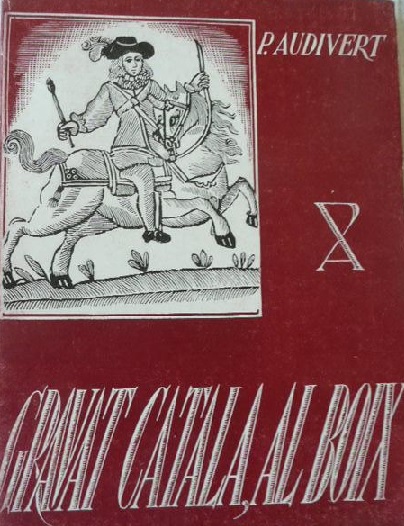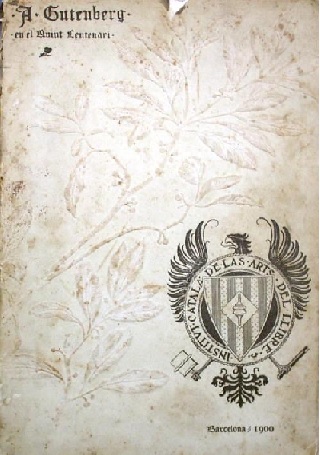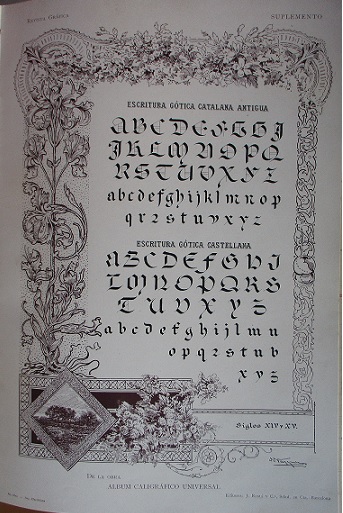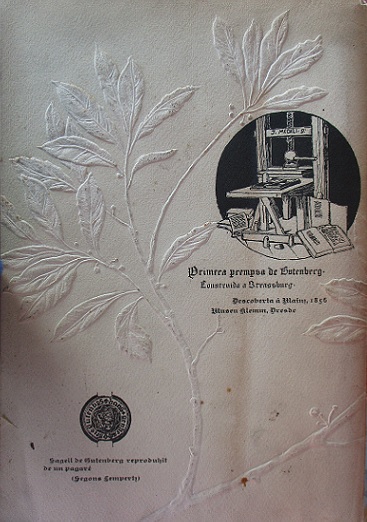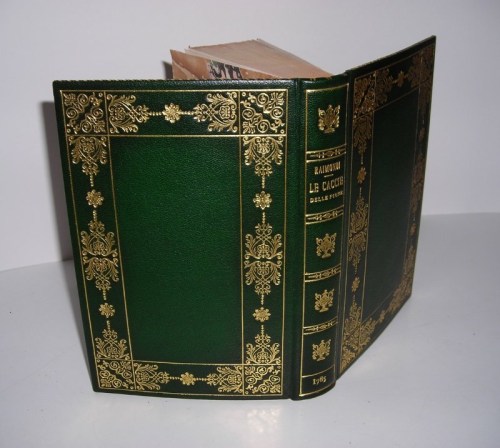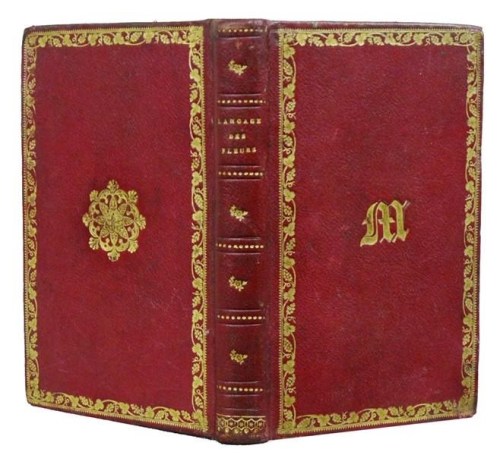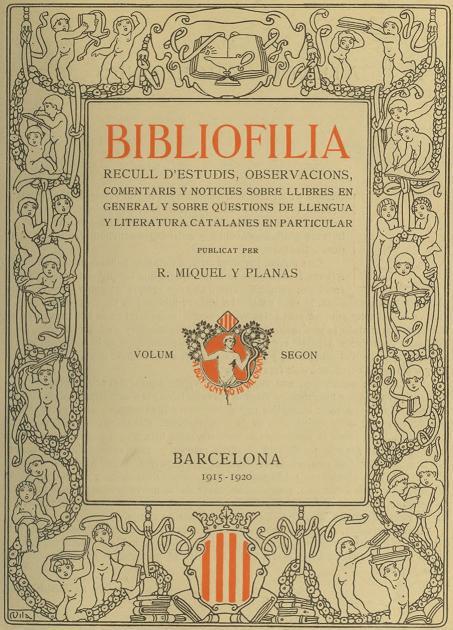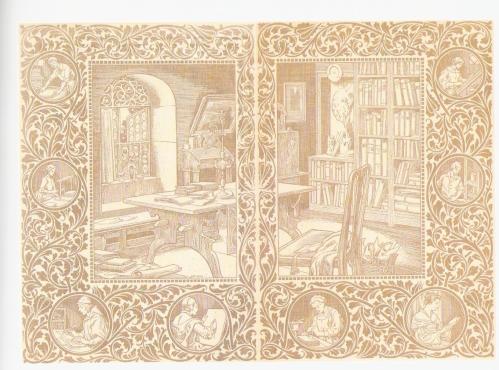
“ És en la xilografia catalana on trobarem sempre la plenitud d’una imatge que té molt de llegenda; és l’expressió serena, sempre assaonada per l’alè de la terra. Catalunya, poble d’artesans, on els oficis, àdhuc els més rutinaris, sempre han tingut la més bella i acurada perfecció, és un dels llocs on el gravat al boix tingué més tradició, una tradició de segles de treball, una recerca per dir quelcom per mitjà de l’estampa impresa, és la superació d’un ofici ple de dificultats, vençudes amb tota noblesa, en el qual es palesa la personalitat de tot un poble.
La imatge en els boixos catalans és una de les més riques. El tema podrà ésser sempre el mateix, però en la repetició la imatge serà sempre diferent: Mirem si no una estampa de Sant Jordi, tantes vegades repetida, i sempre diferent: és la concepció de l’espai dintre de la imatge, són els petits moviments de línies i formes, amb el complement de diferents perspectives, és sempre la visió personal de l’objecte que s’interpreta, allò que li dóna plenitud de cosa feta, modalitat ben catalana.
Composició serena, expressió de sentiment popular, perquè parla el llenguatge del poble i es troba dintre del poble, composició d’artesà, que, dintre de la seva ingenuïtat, té una idea certa de la importància i valor dels blancs i els negres en l’estampa, és d’un home desinteressat que està al marge del intel·lectual, és l’expressió venerable d’un artesà anònim que ens parla sempre amb les seves mans plenes de saviesa.
Aquesta demostració de la imatgeria nostra és ben catalana, car si comparem els nostres boixos amb els dels d’altres països trobarem sempre una diferència substancial. Els italians seran més clàssics, més afinats, sempre producte d’un sentit d’escola; els alemanys i els holandesos, concrets, sàviament saturats d’una imatgeria rica, espremuda fins a la última gota, és l’obra acabada de l’artista que s’expressa per mitjà d’un ofici portat al màxima perfecció a fi d’aconseguir l’obra. En ells ho trobem tot fet, no tenen aquella mena de suggestió que té el boix català que fa que el que el contempla sempre pugui afegir-hi quelcom més: és la insinuació d’una cosa que no acaba mai d’expressar-se i sempre s’hi troba present.
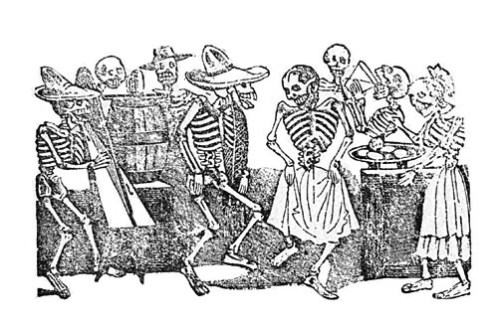
José-Guadalupe Posada, El Jarabe en Ultratumba
I és que mentre en altres països el gravat fou gairebé sempre treballat per artistes que en feren un ofici, adés realitzant les seves obres, adés reproduint les dels altres, a Catalunya seguia essent la feina d’un artesà anònim que interpretava les imatges d’un dibuixant, era la col·laboració de dos homes que es nodrien de les inquietuds i gustos del seu moment.
Aquestes inquietuds, expressades moltes vegades fent concessions als gustos del poble, és el que dóna un caient tan humà a les xilografies catalanes, s’alimenten de saba popular, tenen tota la ingenuïtat de voler agradar i estan fetes amb una saviesa que fa que les puguem apreciar com verdaderes obres d’art sense que llurs autors s’ho hagin proposat. Aquesta diferència substancial amb l’obra preconcebuda fa que hom pugui elevar-la a la categoria d’art pur”.
Gravat català al boix, amb seixanta reproduccions, quatre gravats originals i una auca d’arts i oficis, Pompeu Audivert, Biblioteca Catalana – México, D.F./ B. Costa i Amic Editor, 1946; p.21-22.
Marca d’impressor d’Aldus Manuzio
“ Los que como Ud. Somos aficionados a librajos y papeles viejos, solemos experimentar de vez en cuando algo de esa alegría y emoción inefables que sintieron nuestros esforzados navegantes al descubrir por vez primera las playas del Nuevo Mundo. ¿ No es verdad, amigo mío, que cuando por acaso, en medio de un montón de inepcias condenadas al nacer a rodar por baratillos, a ser pasto de ratones o a envolver cominos, tropezamos con una Aldo Manucio, un Gryphio, un Plantino apud Moretum, un Caxton, …, o con alguno de esos incomparables y codiciados Elzevirios, … gozamos de una felicidad suprema, que comparada con esas grandes pasiones destinadas a satisfacer algunas raras veces y por breve momento el corazón humano, excede de todo un cielo a los goces del amor, de la ambición y de la avaricia? – Cierto es que para el verdadero bibliófilo ( que no se confunde nunca con el falso, el pseudo-bibliófilo, el coleccionador que sólo busca y colecciona por el gusto de atesorar, que en medio de su espléndida biblioteca se aparece al eunuco entre las odaliscas de un harén: el mercachifle literario que adquiere para revender y lucrar; el tonto, pues de todo hay, que tiene libros por aparecer discreto); para el bibliófilo auténtico, para el amateur pur-sang, como dicen los franceses, el hallazgo de un libro raro o de un manuscrito curioso es superior a cuantos juguetes y brillantes señuelos se han inventado para entretener y atraer y fascinar las miradas de esa caterva de niños grandes que se agita y afana en este pícaro mundo, el que, dicho sea de paso, sería una trastienda del infierno, si no hubiera libros.”
Article: “Entre el conocimiento y la bibliofilia”, de Fco. García-Jurado, reproduïnt un text de Camús. En el vlok Reinventar la Antigüedad: https://clasicos.hypotheses.org/317
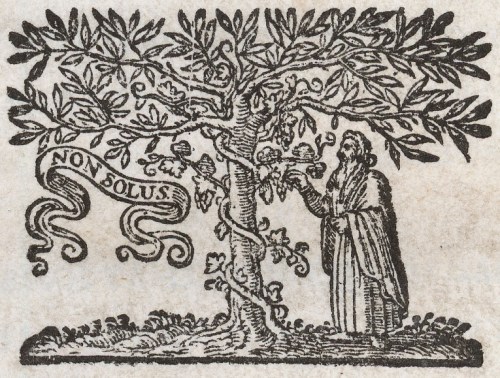
Marca d’impressor d’Elzevir
Revista Gráfica 1900
“ Ja fa alguns anys que tot quan se refereix á las arts anomenadas de una manera general Arts del llibre, es obgecte de particular atenció, y res d’estranyar es que aixís sía; ans al contrari, inesplicable resulta que per tant temps lo trascendental invent de l’Imprempta hagués devallat tant al desota de las demés produccions del home en totas las brancas de l’Industria. Aqueixa s’ha vist sempre, en més ó en menys, á través dels capritxos incoherents de la moda, abellida per les aplicacions decorativas de las arts plásticas. Mentres se pretenía exornar lo més vulgar y prosaich obgecte, necessari en las prácticas de la vida, lo llibre, lo vehicul de la idea, de totas las doctrinas, fconcretament, no solsont de las evolucions que tot ho capgiran, impuls de tots los avensos, doll inacabable de sanitós plaher que enlayra á l’inteligencia, ferm consol del que sofreix, sanitosa distracció dels felissos pobres d’esperit, y en mitj de tot, nombrosa reunió d’industrias, de travalls en que s’afanyan milers de criaturas fent trasbalsar milions, fonament de moltas fortunas; lo llibre, originat y nascut de un procediment artístich; lo llibre, que en son comens era un joyell, había acabat per esser un producte industrial groller y xavacá, fora de raríssimas excepcions ab que distingidas personalitats mantenían la tradició dels bons temps de l’Imprempta, fentne esperar una salutable regeneració, que, si no es arribada á realisarse en tot, se iniciá no fa molts anys, y s’exten, creix y se desenrotlla, comensant a posar lo llibre al nivell de las demés obras del home, no sols concretament com travall d’impressió, sino també en tots los procediments y materials que intervenen en los elements que d’ell se’n derivan.
Revista Gráfica 1900, anunci.
Lo despertament ha sigut ben general: lo meteix á l’América del Nort, á França que á Inglaterra, que á Austria, que á Alemania y que á Italia. Com succeheix en las demés aplicacions de las arts als productes industrials, que l’observació y l’estudi de las obras creadas en épocas ja llunyanas dona per resultat lo formar un comensament d’istil propi de la nostra, la devoció als exemplars de las primeras prempsas contribuheix á retornar al llibre d’avuy quelcom de las qualitats que aquells tenen, y de nou, tot quan s’hi relaciona, tendeix á esdevenir un travall artístich en lloch d’esser lo mer resultat de un ofici manual en que la inteligencia y lo sentiment de la forma, del color y de l’armonía poch ó res tenen que veure.
Dintre de la tradició establerta per las obras clásicas de l’Imprempta, ne deriva, lo meteix que de tots los caracters escrits, més ó menys exótichs, la imaginació d’avuy, tipos y formas que responen al afany de produhir alguna cosa nova; camí que á l’avenir conduhirá indubtablement á la creació de l’original que are tant admirém en lo de sigles enrera”.
J. Lluis Pellicer, en l’editorial de Revista Gráfica 1900, p.1-2; editada per l’Institut Catalá de les Arts del Llibre.
( curiosament, per les més de 40 pàgines dedicades a anuncis ja val la pena la revista)
Revista Gráfica 1900 ( revers)
χφ               χφ               χφ               χφ
Enquadernació de Vicente de Diego
“ Hay muchas clases de libros y  no todos necesitan ni merecen amor. Los hay de usar y tirar; no faltan los que se reducen a simples ajustes de cuentas con otros o con uno mismo; algunos no valen más que como mensajeros; otros no son más que cestos de noticias y los hay cuya existencia no está justificada más que para su autor. Pero los hay también de leer y guardar, para volver a descansar en ellos; de tener, para entrar y salir de ellos; de guardar, para convivir. Y, para ser libros de amar por sí mismos, todos ellos necesitan un lecho acogedor y suave para una tipografía discreta, variada y elegante; una distribución del texto armoniosa y ajardinada; acaso unos complementos gráficos que acompañen sin distraer ni aturdir; un formato que no les impida ser un objeto eventualmente a mano y una encuadernación ( industrial, artesana, fina, original) hermosa. Resultan todavía insustituibles en la vida del hombre de cultura, que hoy pudiera ser cualquiera. No hace falta pedir lo imposible. Sólo un pergamino rubio y blando, más bien sin arrugas, o blanco y duro, ‘ a la romana’, pero sin tensiones deformadoras; una pasta española, acaso jaspeada, con guardas de papel de ondas o de guijarros; un papel labrado o pintado sobre un folleto del XVIII; ojalá, quien pudiera, una pasta valenciana; o un tafilete azul, verde, con frecuencia rojo con un filete en recuadro y cuatro florones dorados en las esquinas. A partir de ahí, todos los sueños. Gracias a la encuadernación el libro es una fiesta. Y no sabría decir si el amor al libro – y en buena medida, la cultura- empieza o termina en la encuadernación”.
Encuadernación y destino del libro ( Loa y guía de pequeños y grandes coleccionistas)”, article de Manuel Carrión Gútiez, a Bibliofilias ( Exposición con motivo del 38º Congreso Internacional y 21ª Feria Internacional de ILAB, Madrid, 2008), pp. 65.
Estampació d’època en plena pell, tafilet vermell, amb estampacions en or en cobertes i llom.
Read Full Post »
Miquel y Planas, durant els anys del periple de Vila, inicia i elabora la seva revista intitulada BIBLIOFILIA. Diem ‘seva’ amb una doble intenció, car no només n’es l’editor, sinó també l’autor de tots i cadascun dels articles. És una mena de petita enciclopèdia sobre el llibre en general i, en particular, sobre qüestions de llengua i literatura catalanes, en què l’autor manifesta el seu coneixement del tema.
Iniciada al juny del 1911, el primer volum abraça tota la producció des del 1911 fins al 1914. Tot i que la il·lustració no hi és important, s´hi reprodueixen alguns gravats facsímils d’edicions antigues. Però allò per la qual cosa se la reconeix sobretot és la portada. L’autor n’és Joan Vila.
Una orla d’amorets enjogassats amb una colla de llibres i entortolligats amb cintes i amb garlandes de flors, presidia al capdamunt per un llibre i un llantió, símbols del saber, i a la part inferior per l’escut de Catalunya, emmarcat el títol i el logotip de l’editor, amb la seva cèlebre màxima ‘A bon seny no hi val engany’ Els amorets de Vila acabaran sent un element clarament identificador seu als llibres de bibliòfil de Miquel y Planas. Perquè no sols en dissenya l’obra, sinó que hi crea un alfabet de caplletres decorades on l’element ornamental és un amoret. Al primer volum de BIBLIOFILIA, la intervenció de Vila es limita a la portada esmentada, a la caplletra A del frontispici, impresa en vermell, i a la taula de noms final, on apareixen totes les caplletres dels amorets.
En canvi, el segon volum, del període 1915-1920, presenta una portada idèntica i una caplletra C al frontispici, però, a més, tots i cadascun dels articles s’enceten ja amb una caplletra. La decoració, doncs, en aquest cas és molt abundant. I no sols això, sinó que també sorgeix un nou element decoratiu que forma part de la mateixa sèrie: quatre capçaleres i tres vinyetes d’amorets jugant amb llibres, pintant-los, tirant-se’ls pel cap, etc., tot emmarcat per les mateixes cintes i garlandes esmentades abans, que es poden veure a les taules d’articles, d’il·lustracions i de noms. D’una gran agilitat i un moviment subtil, aquestes figures atorguen un caire molt peculiar a la revista de Miquel y Planas.
Ara bé, no sols és Vila qui contribueix a fer possible aquesta publicació. Les guardes són a càrrec del seu mestre, Josep Triadó, i les cobertes en relleu de color roig, són obra de Joaquim Figuerola. Quatre noms que, com comprovarem al llarg d’aquestes ratlles, mantindran sempre una relació”.
D’Ivori. Bibliofília i exlibrisme”, de Pilar Vélez en el llibre: D’Ivori. La màgia de la il·lustració, de Josep M. Cadena, M. Castillo i Pilar Vélez. Editat per l’ Ajuntament de Barcelona, dins la col·lecció El traç que alliçona (nº 2),p.
℘          ℘          ℘          ℘          ℘          ℘          ℘
La bibliofilia, desde luego, es un hecho de todos los tiempos. Los testimonios encarecen a los bibliófilos de Alejandría, las bibliotecas inestimables de los humanistas de los siglos XV y XVI – recuérdese, por ejemplo, la del Marqués de Santillana, catalogada por Schiff -. Los mecenas arruinados en su afán por acumular libros, los modernos coleccionistas que luchan tanto con el precio de los libros como con el espacio para guardarlos, nos hablan de esta pasión y de sus variantes. Y en los días actuales este amor, desgraciadamente, pareciera haber entrado en una faz de posible explotación comercial, con lo que ello tiene de anulador, porque ya no sólo se prefabrican ediciones para bibliófilos, sino además también se especula con la rareza. Por eso Valéry, en el ensayo Livres, confesaba que para él la pasión libresca no
residía en lo raro de los libros. ‘La rareza – escribía – no me afecta excesivamente. No es sino una noción abstracta e imaginaria, si por otra parte no está sólo en casa del rematador. Los ojos no saben que tal ejemplar es único. Tocarlo no alegra, no hace gozar de modo especial. Yo, en caqmbio, quiero los libros sólidos i ‘confortables’ como se los hacía en el siglo XVIII’ “.
CASTAGNINO, Raúl H.: Biografía del Libro. Editorial Nova, Buenos Aires, 1961. Colección Compendios Nova de iniciación cultural, nº 42, pp.123.
Read Full Post »
juvenal
“ Quan els nostres esclaus sàpiguen llegir, ja no seran els nostres esclaus. (Juvenal, 42-125).
“Estima el llibre pel llibre, mes procura que sigui bo”. ( San Jerónimo, 331-420).
“Los libros no oyen, pero hablan”. (Góngora, 1561-1627).
nicolas-antonio
“No hay placer mayor que el coleccionar libros… y leerlos”. (Nicolás Antonio, 1617-1684).
“La lectura ens aparta del món i, no obstant això, com més llegim més ens endinsem en ell”.(Victor Alfieri, 1749-1803).
“Una casa sense llibres és com un jardí sense flors”. (Proverbi àrab).
“La passió pels llibres és la més noble de les passions”.(Ling-Po, 1823-1901).
“Qui nomès llegeix un llibre, no sap més que una cançó”.(Popular català)
“Un bon lector fa un bon llibre”.( Emerson, 1803-1882).
apelles-mestres
“Llibre, amic el més fidel, sempre obert a qui et demana…”(Apel·les Mestres, 1854-1936).
“No digas que un libro es caro si el libro es antiguo y raro”. (Rodríguez Marín, 1854-1943).
“Compra llibres encara que no siguin els meus”. (Bernard Shaw, 1856-1950).
cau-ferrat
Cau Ferrat creat per Rusiñol
“Els llibres, per a mi, no són mai cars ni ‘baratos’, són bons o són dolents”.(Santiago Rusiñol, 1861-1931).
diccionari-aguilo
“He passat la vida entre llibres, i si una altra vida tingués faria el mateix”.(Marian Aguiló, 1835-1910).
“Un bon llibre no es paga en diners”.(Popular català).
bibliophrasis1
Frases de l’opuscle : “ Bibliophrasis. VII Feria anual del Libro de Ocasión. Antiguo y Moderno”, Barcelona, 1958. Obsequio a los favorecedores de la Feria. (Obsequi que ja fa anys que ni donen ni fan).
antologia-de-sitges1
“ Bueno, vamos a abrir las puertas de mis librerías. He insinuado ya que soy un bibliófilo modesto. Aquí no daréis con incunables ni con primeras ediciones. Aquí viene, sencillamente, el buen libro tanto de contenido como de presentación”.
ROBERT MESTRE, José: Divagaciones de un bibliófilo, disertación de … , en la Asociación de Bibliófilos de Barcelona, Barcelona , 1964.
Editat l’any 1965, imprés a Filograf (R.G.M., Instituto de Arte Gráfico de Barcelona), 1965. Opuscle de 7 pàgines amb dibuixos de Emilio Ferrer.
filograf2
exvlokis-color
Read Full Post »
rosa vera 1
“ A partir de 1948 neix a Barcelona una altra iniciativa en el camp de la bibliofília que deixarà una forta empremta. Em refereixo a les edicions de La Rosa Vera, que fan una labor extraordinària en la promoció de les edicions d’alta qualitat, tant de llibres de bibliòfil com de sèries de gravats. La iniciativa parteix del gravador i pintor Jaume Pla Pallejà (1914-1995), i tot se- guit compta amb la bona acollida i el patrocini econòmic del col·leccionista i mecenes Víctor M. d’Imbert. L’aportació a la bibliofília de les edicions de La Rosa Vera és una de les més notables per l’obra realitzada i la promoció que representa de l’expansió del gravat, al qual es van dedicar alguns artistes reconeguts que el practicaven per primera vegada.
rosa vera 2
Jaume Pla destaca no només com a gravador, que domina amb una gran perfecció totes les tècniques i tots els procediments, i com a promotor del gravat i de les edicions selectes, sinó alhora com a teòric d’aquestes matèries en diversos llibres i articles, en els quals es mostra amb uns criteris molt precisos i estrictes, de gran exigència. És un dels pocs que ha exercit en aquest camp una crítica responsable i documentada. En el seu llibre Técnicas del grabado calcográfico ( 1956   la primera edició) van aprendre a gravar moltes persones d’aquí i d’altres països. L’autor, en  un capítol del llibre, teoritza potser per primera vegada sobre el que és la bibliofília: aquest capítol  ha estat una font bàsica per a molts dels qui després hem tingut una predisposició especial per l’estudi i el col·leccionisme de llibres il·lustrats.”
F.X. Puig Rovira, a “Unes notes sobre el llibre il·lustrat al segle XX”, en el llibre Aureum Opus. Cinc segles de llibres il·lustrats. Quaderns del Museu Frederic Marès. Exposicions,5; p.86.
tecnicas grabado jaume pla
“ Para otro experto, son otros los factores que inciden en el valor de los libros. En primer lugar, señala la historia del libro, ‘en la que se incluyen su buen ranking de ventas, su precio, y la opinión de los libreros sobre la seriedad de su contenido’. En segundo lugar, ubica la experiencia propia, y la intuición para reconocer un libro con mucho valor ‘ muchas veces esos libros están escondidos, a un bajo precio, y son muy pocos los que reparan en su alto valor’.
Existe un gran número de factores. El biógrafo John Carter dijo alguna vez ‘ Luego del interés por la belleza o importancia del libro, lo cual siempre fue un parámetro importante, las dos consideraciones más substanciales son probablemente la rareza de la edición y el estado de la copia’.
Para otros, por último, lo más importante en el valor del libro es la oferta y la demanda. ‘Hay muchos factores que inciden en estas variables, pero todo quedará resumido a una cuestión: el precio de tapa’. Entre los factores que afectan a esta cuestión, se encuentran ‘los años que tiene, las ediciones limitadas, el estado, y la firma del autor, pero nada de ello es garantía de su valor: Sólo se determina por cuantos hay en el mercado y cuantas personas desearían comprarlo’.
Article: “Bibliófilos: ¿ de qué depende el valor de un libro?” en el vlok: “En Plenitud, el sitio para mayores de cuarenta”.
rosa vera3
Read Full Post »
La Casa de Hojas en negre i blanc
casacasa
Read Full Post »
catálogo salvá1
“ L’exquisidesa del suport, de la tipografia, del disseny, de les il.lustracions, de la relligadura, etc., son factors que poden influir en la bellesa del llibre motiu pel qual els bibliòfils ho tenen molt en compte a l’hora d’avaluar-lo.
Salvà considerava que els llibres impresos sobre vitel.la i pergamí podien valdre entre 6 i 8 vegades més que els impresos sobre paper i els impresos en gran paper, el doble. Aquesta no és una regla que avui s’apliqui exactament però si que és indicativa de la importància que es dóna a la qualitat del suport emprat per a estampar un llibre o un document”.
mapa beato1
“ De molt antic s’ha il.lustrat el llibre per fer-lo més atractiu i, com no, més amè. El llibre manuscrit s’il.lustrava amb mimiatures molt sovint il.luminades. Diversos exemplars del Beato de Liébana són un exemple paradigmàtic de la bellesa que pot assolir un manuscrit il.lustrat.
Els primers gravats dels llibres impresos foren xilogràfics per passas desprès a utilitzar altres tècniques com la calcogràfica i la serigràfica. A finals del segle XVIII es començà a emprar la litografia ( l’any 1820 a Espanya) i més tard, les tècniques relacionades amb la fotografia.
Sabem que la presència a un llibre d’il.lustracions d’artistes com Albert Durero, Hans Holbein, Vingles, Courbes, Palomino, Carmona, Doré, Picasso, Gris, Maillol, Miró, Dalí, etc., fan que el seu valor augmenti de forma considerable.
hypnerotomachia1
Voldria mencionar aquí el llibre de Francesco Colonna, Hypnerotomachia Poliphili ( El  Somni de Polifilo), imprès a Venècia l’any 1499 per Aldo Manuzio que, en les escases ocasions que ha sortit al mercat, ha assolit altíssims valors per estar considerat com un dels més formosos i cèlebres llibres il.lustrats de la Renaixença”.
Frases de la conferència que el senyor Jordi Estruga, President de l’ABB, va donar al Col.legi Oficial de Bibliotecaris Documentalistes de Catalunya en el curs “Valoració dels documents escrits” l’octubre de 2006.
biblioteca arsenal1
“ La Biblioteca del Arsenal ( rue de Sully) nos propone, hasta el 29 de diciembre, una aventura a caballo entre la necrofilia, el fetichismo, la aventura solitaria y nocturna y el amor más apasionado y mortal: una historia de la bibliofilia, sus desvaríos, sus inconfesables secretos. La exposición parte de una vocación pedagógica muy simple: reconstruir una historia.
Concretamente la historia de los primeros ciento cincuenta años del ‘Boletín del bibliófilo’. Y, a través de esa aventura informativa, asistimos a un proceso mayor: la historia de ciento cincuenta años de una manía que, en el menor de los casos, desemboca en la locura de la posesión, y, en el peor, confina con el crimen.
Baroja reconstruye, en ‘las aventuras y mixtificaciones de Silvestre Paradox’, un caso límite que Buster Keaton o Groucho Marx hubiesen amado con locura: la biblioteca parece confinar con el más fastuoso de los desvanes y con la más fútil de las manías posesivas.
Paradox Baroja 2
Flaubert nos habla de la fisonomía ‘taciturna y soñadora, triste y sombría’ de un pobre tipo que sólo tuvo un amor en su vida: los libros, Flaubert recuerda que ese melancólico personaje ‘apenas sabía leer’…
Se trata, sin duda, de casos límite. Pero… recorriendo esta exposición, el viajero podrá advertir que, en definitiva, no se trata de casos aislados. El mes de marzo pasado, un célebre librero, Pierre Beres, instalado en una dirección célebre, avenida de Friedlan, número 14, pagaba la suma de dinero más alta pagada, jamás, en Francia. Quizá en el mundo, por un libro: un millón doscientos mil francos 8 unos 23 millones de pesetas) por un ejemplar de la edición de los ‘Ensayos’, de Montaigne… La bibliofilia desemboca en la más turbulenta vida comercial.
Essais Montaigne2
Sin embargo, sería totalmente insensato pensar que el bibliófilo paga para acumular capital. Error absoluto.”
Article ( crònica des de Paris) de Juan Pedro Quiñonero en el diari ABC de Madrid, el 14 de desemjbre de 1984, a la pàgina 49, sobre una exposició que feien a Paris.
Read Full Post »
especulum 2 ok
Manuscrit A de l’Speculum al foder (BNM, ms. 3356, f. 35r)
“ La filologia, tret de rares excepcions, acostuma a prestar poc interés a la bibliofilia. Potser perquè es considera que un text acurat i fiable està renyit amb un llibre imprès en bon paper japó o de fil, del amb una tipografia impecable, sovint il.lustrat i a un preu que sol ser alt, com correspon a un desplegament artesanal d’aquesta mena. Filologia i bibliofilia, en una paraula, tenen vies diferents de difusió. I, amb tot, l’univers de la bibliofilia custodia secrets molt ben guardats de la nostra historia lingüística i literaria, tan singular i plena de sotracs de diversa mena. Secrets que criden poderosament l’atenció del filòleg”.
Article d’Anna Alberni: “L’edició en lletra gòtica de l’Speculum al folder (1917). Història d’un misterios exemplar d’infern”, a Llengua&Literatura, n. 17 (2006), pp. 257-282.
especulom 1 ok
Edició en lletra gòtica de l’Speculum al foder (1917).
“ ¿ Quién no ha sentido alguna vez – escribió el último de los citados ( Marañón) – la más noble y profunda envidia en la tienda de un librero?”.
Pero este espíritu va desapareciendo, por imposición del nuevo sentido comercial que trae consigo una vida rápida, mecanizada y múltiple. Y se refugia en esos baluartes muchas veces modestos en que el libro conserva toda su categoría sentimental y es conocido, valorado, acariciado, uno por uno, con exacta medida de su edad y su mérito, de su importancia y su rareza. Librerías de Lance. Librerías de Viejo, Librerías de Ocasión… Oscuras tiendas de entrañas con sabor y tentación de misterio, o tenderetes al aire libre: en unas y otros se alinean o se amontonan los libros que vivieron ya en otras manos, que despertaron sueños e inquietudes en otras fuentes.
En esos comercios, comprador y vendedor ‘saborean’ el volumen, saben perfectamente cuál es su alma. Ese vendedor ama el libro, está al tanto de títulos y autores, sabe cuál es el mérito de una edición rara, conoce los caminos para encontrar un volumen agotado, consigue esa difícil obra que buscábamos desde hace tiempo. los dos, comprador y vendedor, pueden hablar como participantes de una misma fe, como alistados en un mismo amor. Desde Anatole France a nuestro ‘Azorín’ hay una larga lista de escritores que amaron este comercio del libro antiguo. Aquí no ha entrado aún el viento de la nueva organización comercial, y escritor y librero siguen hablando como amigos viejos, de cosas que les son comunes, entrañablemente comunes: este autor, aquella novela, la rara edición de otro tiempo”.
Art. “Elogio y alma del libro viejo” de José Montero Alonso, a Revista de Lllibreria Antiquària, nº 1, pp. 31-32.
el libro y el librero 2
Read Full Post »
ABB 1
“ Dins d’aquesta mateixa línea, la Societat Catalana de Bibliòfils, fundada a Barcelona el 1903, representà el darrer pas de la Renaixença coincidint i formant ja part del Modernisme, moviment, el tret més definitori del qual, a més de la voluntat de modernitat – d’on deriva el seu nom – , fou la integració de les arts i/o la recerca de l’obra d’art total. Amb aquest objectiu, els bibliòfils encarregaren un tipus gòtic a Eudald Canibell, el gran polígraf, el carácter més complet i de més qualitat que es fon a Catalunya en tot aquest período, el denominat avui ’Gòtic Incunable Canibell’,
exlibris RMP
Exlibris Ramon Miquel y Planas. Ex-libris dibuixat per Joaquim Figuerola, amb els motius decoratius tipogràfics del gòtic incunable Canibell
per dur a cap les seves edicions al més acuradament posible. Perquè els bibliòfils vuitcentistes i els primers noucentistes produeixen i editen allò que troben a faltar o consideren necessary per a la cultura del país, tot i que el ressò de la seva labor és reduït car resta cenyit, pràcticament, a llurs biblioteques.
És important recordar com els bibliòfils, portats pel desig d’editar obres antigues catalanes, medievals o renaixentistes, és a dir, portats pel seu caprici, van arribar a encarregar a Canibell el disseny i posterior fosa d’un tipus per tal que les seves publicacions s’adiguessin plenament amb el to del seu contingut. El primer article dels estatuts de l’esmentada societat remarcava el seu propòsit de ‘publicar o reproduir obres catalanes inèdites o rares que tingan interés a Catalunya y als demés reyalmes y territoris de la llengua catalana’.
Continent i contingut, doncs, van de bracet i arriben a constituir una obra d’art total. És realment un cas força excepcional, fins i tot, o primer que tot potser, per l’esforç econòmic que això va representar, tot i que el mateix Canibell ja havia dissenyat un Gòtic Tortis. Però pot afirmar-se que el Gòtic Incunable Canibell amb els cossos 8, 12 i 24, més unes inicials monocals de cos 24 és l’únic carácter tipogràfic autòcton del Modernisme. La tipografia neogòtica és, doncs, decisiva i contribueix a donar el to d’obra total a aquest llibre de bibliòfil, molt poc il.lustrat”.
VÉLEZ, Pilar: “ El llibre a la darreria del Vuitcents: eina de cultura i progres i obra d’art total”, dins L’exaltació del llibre al Vuitcents. Art, industria i consum a Barcelona, BC-Ajunt.Barcelona, B, 2008, pp. 298.
exaltacio llibre vuitcents
“ Esta literatura modalizada, redefinida, suscita su propia literatura: discurso aplicado ( dónde colocar la Bibliothèque curieuse de Gabriel Peignot o la Theorie des éditions elzéviriennes de Nodier) o literatura secundaria ( llamamos así a todo lo que se ha podido escribir sobre las bibliotecas: catálogos que han adquirido una existencia propia y son importantes por sí mismos, como The Rowfant Library de Frederic Locker-Lampson, autor, célebre en su época, de los London Lyrics, pero que más tarde sólo ha sobrevivido, siguiendo un ejemplo clásico, gracias al inventario de su biblioteca, convertido en un clásico de la investigación en este campo).
rowfant library3
Los miembros de esta hermandad secreta se relacionan entre sí, por otra parte, a través del correo de los catálogos de venta que los libreros publican a intervalos regulares. Resulta fácil aislar en ellos, cuando se los examina, uno de esos signos discretos – una característica suplementaria- por medio de los cuales un grupo nunca deja de reconocerse a sí mismo. Se trata de la notable importancia que esos boletines otorgan a una literatura generalmente poco leída – desde el momento en que esta cultura tranquila ya no refleja la jerarquía de valores del hombre de bien, ya no respeta las proporciones -: la literatura medieval y renacentista.
Un gusto de esta clase – que lleva a multiplicar las ediciones ilustradas ( por mencionar sólo a los más considerables) de Rabelais y de Villon – no se contenta con expresarse de esta guisa, en un ( muy relativo) desbordamiento de pasión; por el contrario, parece que se extiende por mimetismo; y la cultura bibliófila se constela, de muy buen grado, de goticismo. El librito para principiantes de Jean Marchand – bibliotecario y bibliófilo célebre de los años cincuenta – se titula, por ejemplo, Epîtres a un ami bibliophile;
epitres
y en él el autor se da a sí mismo el nombre de Johannès Mercator; los capítulos van precedidos de argumentos escritos en una lengua ( y una tipografía) arcaica; el estilo se mantiene siempre igual de ‘sabroso’ (‘ y si un día hubieras de separarte de él ( lo que no te deseo) – escribe Marchand a propósito de un libro raro-, que sea al menos a cambio de tus buenos luises contantes y sonantes, de tus doblones y carolus de lealtad probada’); por último, se dedica todo un capítulo a la necesidad de restablecer la ciencia prestigiosa y en desuso de la heráldica, emblema perfecto de lo medieval.
Así pues, el bibliófilo se parapeta tras un lenguaje ostensible y supremamente arcaico ( y castizo), tras un barniz de pureza, un vocabulario exasperado y altanero que expresa al mismo tiempo una arrogancia aristocràtica ( bien es verdad que demasiado ostentosa para ser vàlida) y el deseo de refugiarse en unpaís sin historia, anclado en unos orígenes gloriosos. Todo ello dentro del marco de una economía de la apropiación nunca lo bastante rígida y, si lo pensamos bien, de naturaleza eminentemente ficticia: ‘Una vez que se ha efectuado el descubrimiento – constata Marchand -, que el libro ha sido ya catalogado, estudiado como es debido y colocado en su anaquel, la historia ha concluido’. Hay que construirse otra, sacarle todo el jugo, y así hasta el infinito”.
“Anatomía del bibliófilo”, de Patrick Mauriés, traduït per A. Taberna, a Revista de Occidente, nº 141, 1993, pp. 88-89. ( Original a Traverses, Paris, 1983).
Read Full Post »
“ Entre els punts de distribució de llibre antic, a més de les llibreries i de les cases de subasta, tenen certa importància les fires i els salons, que concentrant l’oferta produeixen l’atracció d’aquells que desitgen adquirir i conèixer el llibre antic. Les fires están pensades pel públic en general, mentre que els salons están dirigits als professionals del comerç del llibre i a un conjunt molt escollit de clients. També es poden incloure en aquest mateix nivell comercial les ciutats del llibre que es constitueixen, en realitat, com a fires permanents del llibre, tot i que amb característiques especials de desenvolupament rural i atracció d’un turismo cultural”.
Art. “Comerç i taxació del llibre antic” de Manuel José Pedraza Gracia,a Item, n. 51, jul-des 2009, p. 121.
Diferents Fires
“ Aspira nuestro Conservatorio al sostenimiento de todas las artes relativas al libro, pero especialmente de aquellas que a causa de la tendencia estandarizante de nuestra época, y con grave perjuicio para un futuro próximo, corren el peligro de desaparecer
Se equivocaría, sin embargo, quien supusiese en nosotros una desviación hacia la Bibliofília, entendida como culto del lujo, de la rareza o de la riqueza material en el libro. Sin excluir, en las artes que conciernen a éste, lo que les puede convenir en el aspecto suntuario, interesan fundamentalmente a nuestro Conservatorio – y en este sentido se hallan organizadas sus enseñanzas – los que podrímos llamar valores indeclinables para la dignidad del libro, de su presentación y conservación. La sencillez, no es sólo compatible, sino muchas veces indispensable, a esa dignidad. Y la selección y calidad, son independientes en absoluto de la rareza, cosa evidente, al menos, en los aspectos tipográfico y calcográfico, que son los que justifican los más individualizados valores de la encuadernación
Nada podrá separarnos de esos principios. Reflexionando atentamente sobre la situación y tendencia actual de la producción librera, se echa de ver que su misma mecanización y progreso le imponen unos límites que habrán de repercutir cada día más en beneficio de las artes del libro propiamente dichas. Por lo pronto, la edición de códices antiguos y la reedición de libros raros y agotados, se hallan hoy considerablemente colapsadas por una apelación cada día más frecuente  al microfilm. No tardará este procedimiento fotográfico, que alcanzará, sin duda, mayor perfección, a trascender de una manera sensible sobre la producción librera en general. Porque si en los casos apuntados, las rzones para el uso del microfilm dimanan, en rigor, del enorme riesgo económico que supone la edición de obras de muy limitada circulación, han aparecido también, y de día en día son más compartidas, las razones que aconsejan el mismo uso del microfilm, apoyándose en la falta de espacio para la conservación de los libros. Son bastantes las bibliotecas, hoy, sobre todo en Norteamérica, en las que, para determinadas obras, se prefiere – permítasenos la frase – el celuloide a la celulosa, es decir, el microfilm al ejemplar impreso que se halla en el mercado.
El microfilm supone la existencia del libro. En esa misma existemcia estriba otro procedimiento fotográfico ensayado en los Estados Unidos, que es el de la placa de tamaño normal, capaz, cada una, para reproducir algunos centenares de páginas de libro No sabemos cuál será el porvenir de este sistema. Pero lo cierto es que tales procedimientos parten del libro, en la forma que le ha dado la imprenta, bien que no sólo frenando, sino haciendo retroceder considerablemente la cifra de las tiradas.
¿ Cuál será la consecuencia de este retroceso? No parece de difícil previsión. La industria librera se verá obligada a reforzar, en gran parte, las calidades artísticas de su producción, ya que será en función de éstas y no de su potencial mecánico, que esa industria podrá sostenerse, dando al libro impreso – combatido también por el cine, la radio y el disco – categoría de objeto destinado a minorías cada vez más especializadas y exigentes. Es decir, en la época del microfilm, el libro impreso conocerá su magnífico renacimiento artístico. Volverá a adquirir ese rango de cosa personal y entrañable que equivocadamente se ha supuesto, a veces, en trance de inmediata bancarrota.
Nuestro Conservatorio inscribe, pues, sus actividades en una acusada tendencia de nuestra época. Y por ello en él se cultivan con noble atención la tipografía y la encuadernación clásicas y modernas, el grabado sobre madera y sobre metal, la litografía, la restauración, etc. Más que nunca, para la defensa del libro, es hora de estudiar, en la realidad actual y en su perspectiva histórica, sus factores artísticos y sus técnicas”.
Article de J.B. Solervicens: “Conservatorio de las Artes del Libro”, a Ensayo, nº 10,  Butlletí de l’Escola d’Arts i Oficis Artístics de Barcelona, 1958, pp. 14-16.